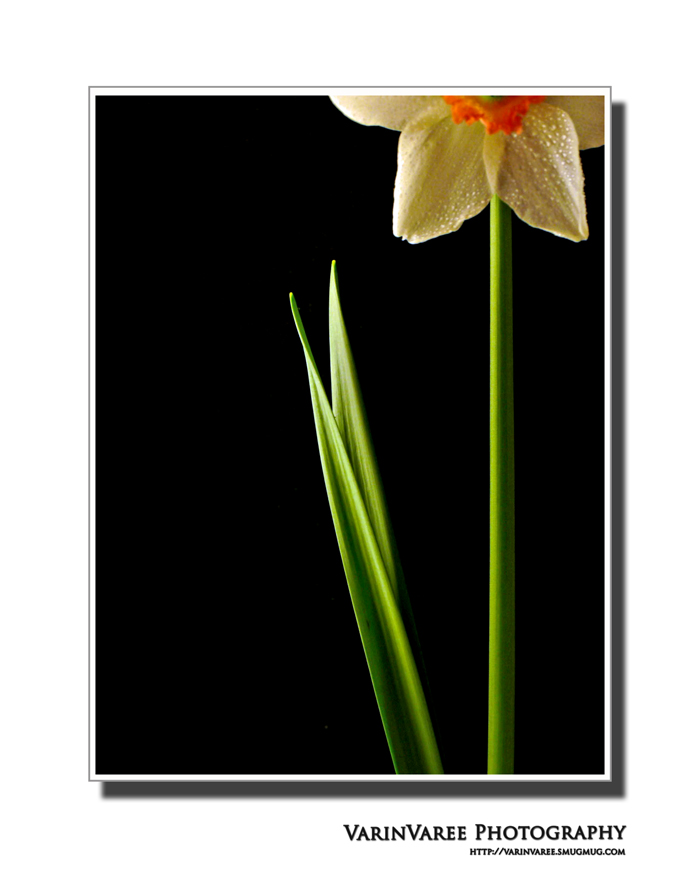
กระจู๋แสดงภาพ...ดารา
กรอบกว้างไม่เท่ากันด้วยค่ะลุงโก้   :27:
แต่แบบนี้สวยดีค่ะ เรียบๆดี  :25:
มาแว้ววววว จ๊ะ ดาราลองทำแบบที่หลาย ๆ ท่านพูดมานะคะ
(ยังไม่ล้มเลิกค่ะ)
ชอบขึ้นอีกหน่อย
บ้ากรอบ  :43:
ลดความเข้มของตัวหนังสือลงอีกนิดก็ดีครับ  :52:
ลดขนาด ตัวหนังสือนักหน่อยก็ดีน๊า  :25: